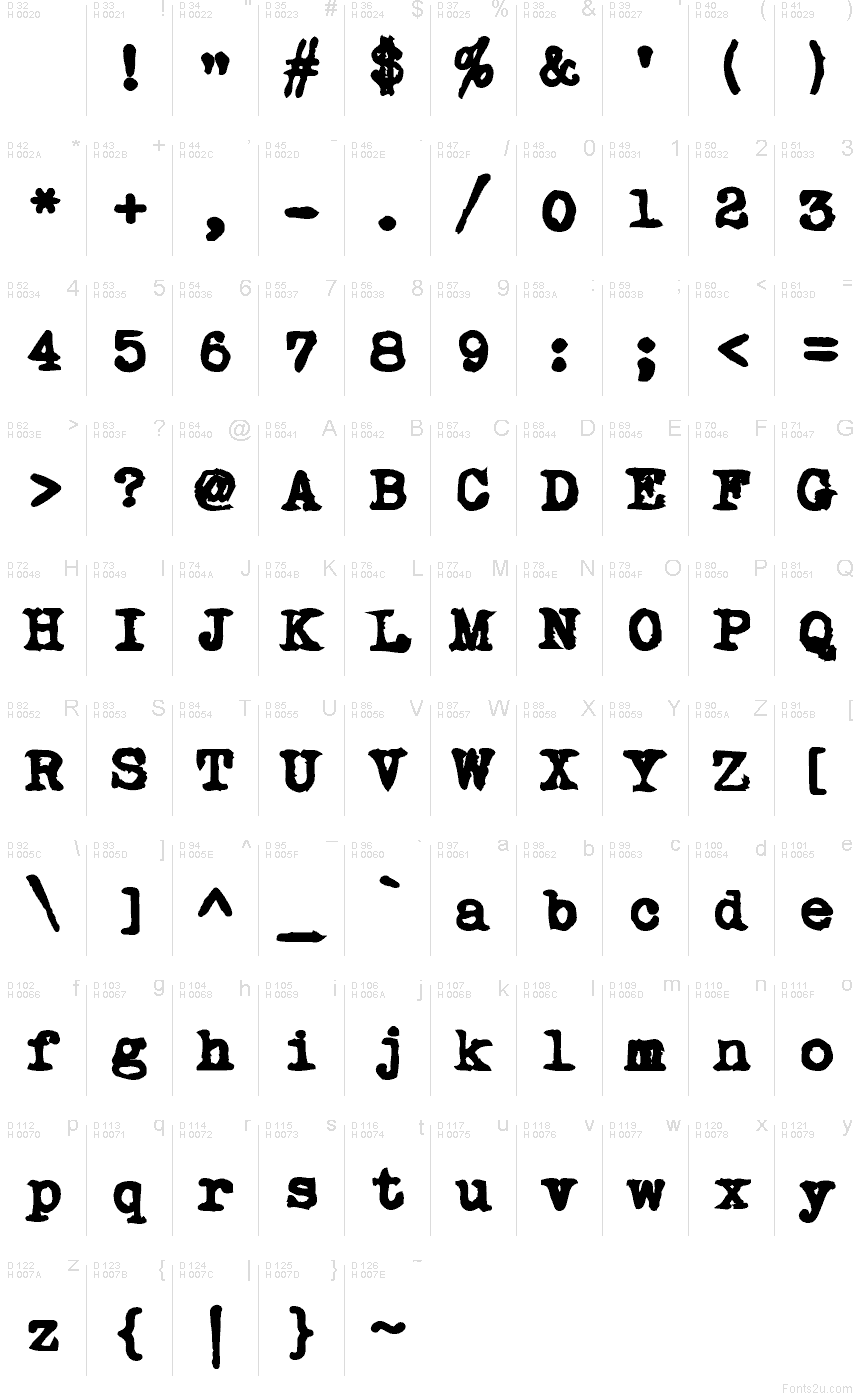
My Underwood Pro Bold
Ma police Underwood Pro Bold est une typographie display gratuite au style érodé, caractérisée par des empattements massifs et des bords irréguliers qui donnent à chaque tracé un aspect brut, comme découpé dans le bois. Les lettres conservent une structure robuste et classique, mais les contours ébréchés et irréguliers adoucissent le dessin, conférant à l'ensemble une allure artisanale plutôt que polie.
Underwood Pro Bold fonctionne à merveille pour les titres d'affiches, les packagings vintage, les couvertures de livres, les logos et les visuels événementiels qui réclament une identité serif marquée par le temps. Cette police gratuite est également parfaite pour le design d'étiquettes et les titres décoratifs, car sa finition érodée apporte de la texture et une patine ancienne tout en préservant la force de la forme serif sous-jacente.
Underwood a été mise à jour pour inclure un grand nombre de caractères ainsi que des alternatives standard. Des réparations ont été apportées à la police.
Une version regular est également fournie avec cette mise à jour.